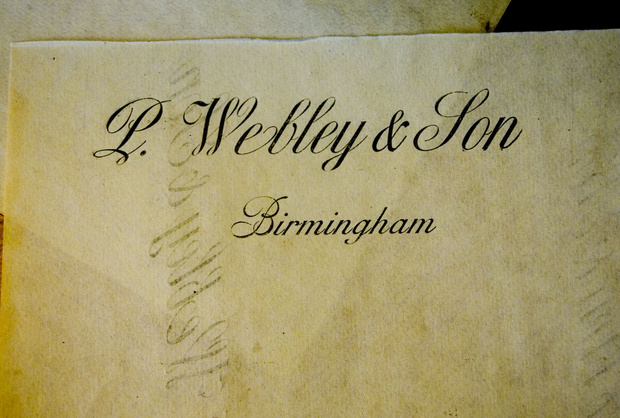
Bleisatz 19. Jhr. script
Kann mir jemand mehr zu dieser Schrift sagen, und wie bzw. in welche Familie man sie einordnen könnte?
Zu dieser Bleischrift kann ich sagen dass sie in verschiedenen Grössen um 1900 an eine französische Druckerei geliefert wurde.
Es besteht kein Hinweis auf eine Giesserei.
Der erste Versuch auf dem Foto wurde auf antikes papier gedruckt.
Ich beabsichtige damit ein Etikett für einen englischen duellpistolenkasten um 1855 zu entwerfen und zu drucken bei dem das Original fehlt.
Ich möchte auch mit dieser Schrift ein Messingmedaillon mit dem Namen des heutigen Besitzers gravieren.
Meine nächste Frage wäre gewesen ob Sie denken dass diese Schrift zu dem Projekt passt.
Des weiteren möchte ich neben dieser "haupt" Schrift ein paar erläuternde Worte wie eine londoner Adresse einfügen.
welche Schrift würde dazu passen? Ich dachte an eine Antiqua.
Ja, eine klassizistische müßte es sein, die den Strichstärkenkontrast der Schreibschrift aufnimmt.